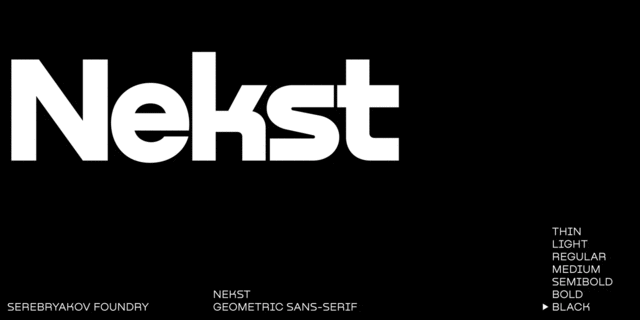
Некст – это геометрический шрифт без засечек. Так может показаться на первый взгляд, но нестандартные формы некоторых букв выглядят неожиданно и эксцентрично в текстовой строке. Эти формы добавляют нотки старого гротеска и футуристической эстетики к современному нордическому образу. Шрифтовое семейство Nekst включает семь начертаний, поддерживающих кириллицу и расширенную латиницу. Шрифт разработал Денис Серебряков в 2020 году.
тяжелый, тесный, мощный, авторитетный, внушительный, серьезный, убедительный, твердый, железный, надежный, мужественный, уверенный, стальной, грубый, стабильный, громкий, ровный, сильный, кондовый, устойчивый, важный, точный, прямоугольный, индустриальный, техногенный, монументальный, урбанистический, мотивирующий, суровый, крутой, амбициозный, городской, жесткий, резкий, четкий, урбанистичный, статичный, практичный, крепкий, автоматический, искусственный, машинный, инженерный, железнодорожный, чертежный, солидный, самостоятельный, ответственный, добротный, технический, архитектурный, футуристичный, космический, спортивный
машиностроение, завод, металлургия, тренажеры, станок, инструмент, строительство, стройматериалы, склад, порт, архитектура, конструктор, чертеж, техника, промышленность, электростанция, энергетика, ремонт, урбанистика, депо, каска, униформа, вагон, авиация, самолет, стройка, обувь, грузовик, мотор, двигатель, город, сталевар, инженер, автоматика, пресс, дизайн, сейф, охрана, защита, робот, железная дорога, архитектор, технологии, локдаун, фантастика, машина, внедорожник, игра, айтишник, айти, IT, транспорт, автомобиль, топливо, космос, киберспорт, спорт, дальнобойщик, доставка, одежда, нефть Стилистика: